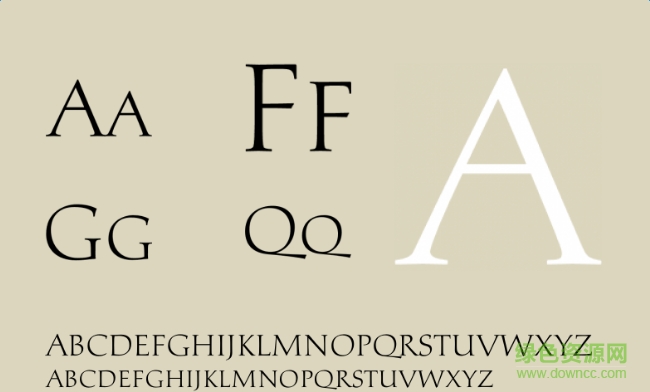
palatino nova titling字體是一款常用于海報(bào)、雜志、廣告設(shè)計(jì)等方面的正文。字體結(jié)構(gòu)端整,字形清新優(yōu)雅,喜歡的朋友快來綠色資源網(wǎng)下載吧!
palatino nova titling字體的字符間距和比例相當(dāng)?shù)膭蚍Q,字體優(yōu)美大氣,可讀性十分優(yōu)良,可廣泛應(yīng)用于商業(yè)領(lǐng)域!